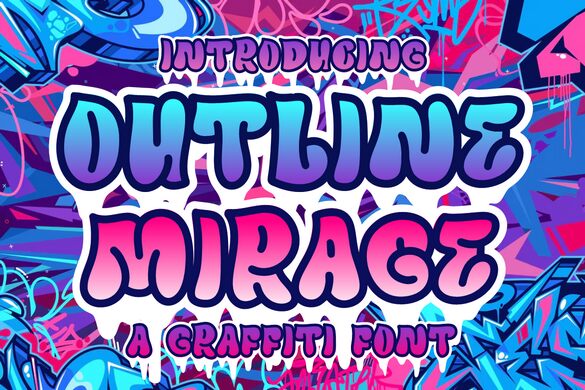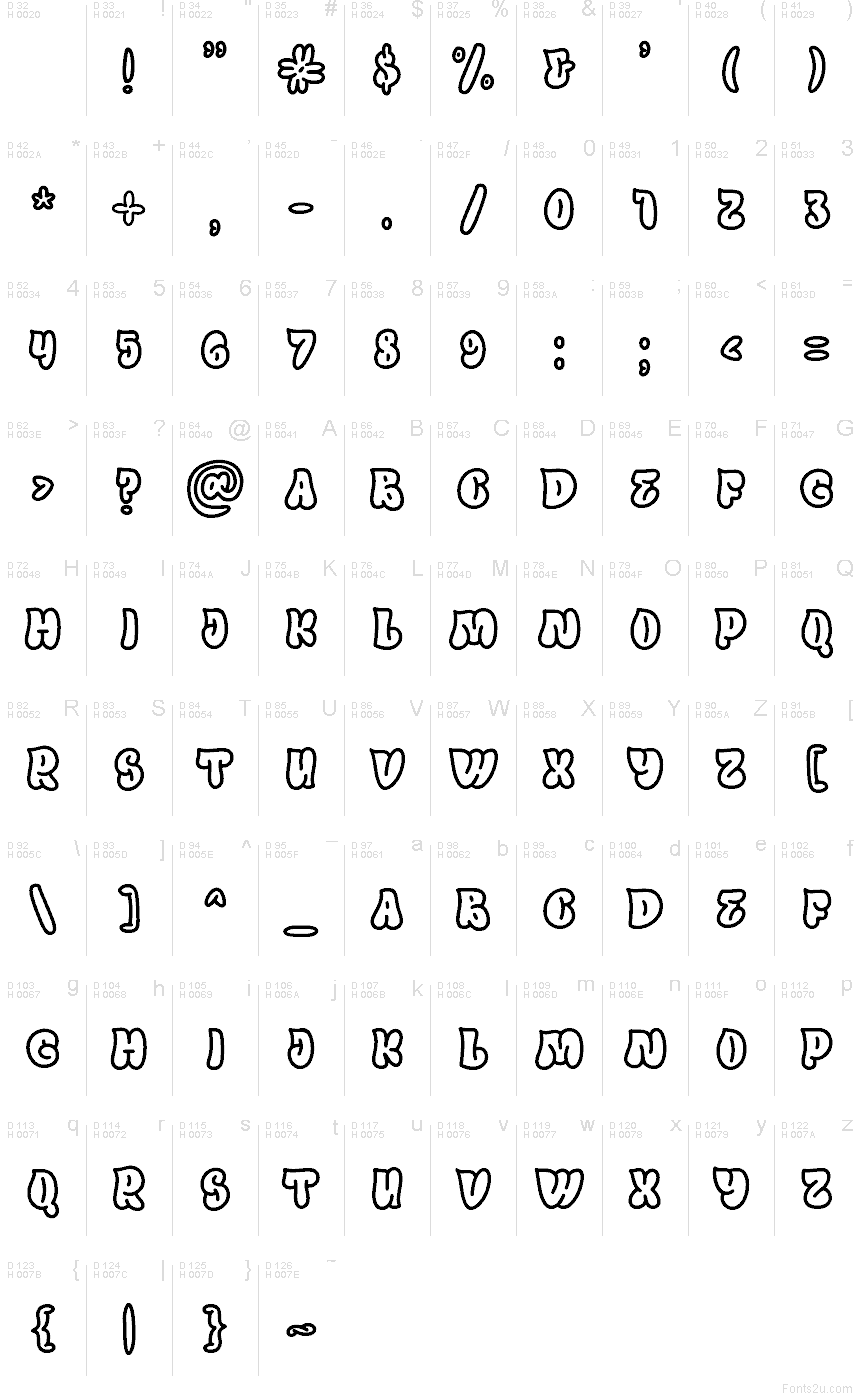
Outline Mirage Line
Shanaf StudioによるOutline Mirage Lineは、太いアウトラインが特徴のバブル・グラフィティ系フリーフォントです。ストリート感あふれるラフな仕上がりで、文字はぷっくりと柔らかいフォルム。太い黒の輪郭と丸みを帯びた角、そして少し不揃いなリズムが、洗練されすぎないカジュアルな雰囲気を演出します。
ポスターや音楽関連のアートワーク、スケートやストリートウェアのグラフィック、タイトルカード、インパクトのあるSNSのヘッダーなど、短い文字数で世界観を伝えたいシーンに最適です。ぷっくりとしたアウトラインは、ロゴのスケッチやモノグラムなどにも自然に馴染み、塗りつぶしなしでグラフィティ特有のエネルギーを表現したい場合にぴったりのフォントです。